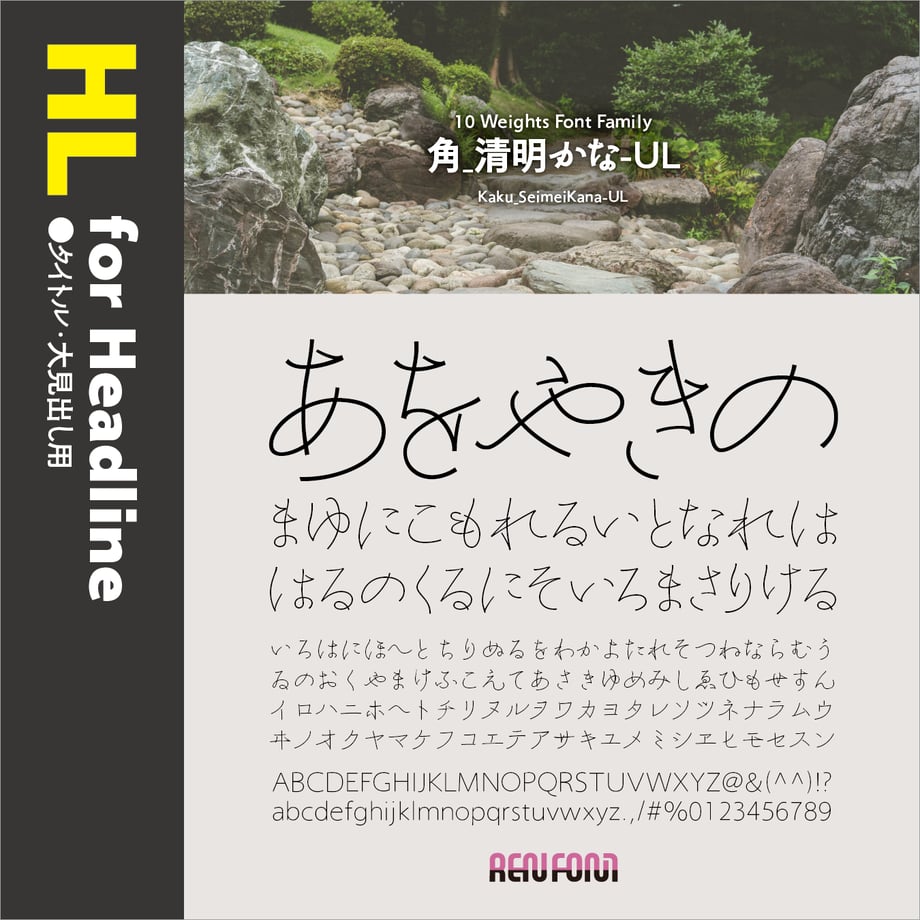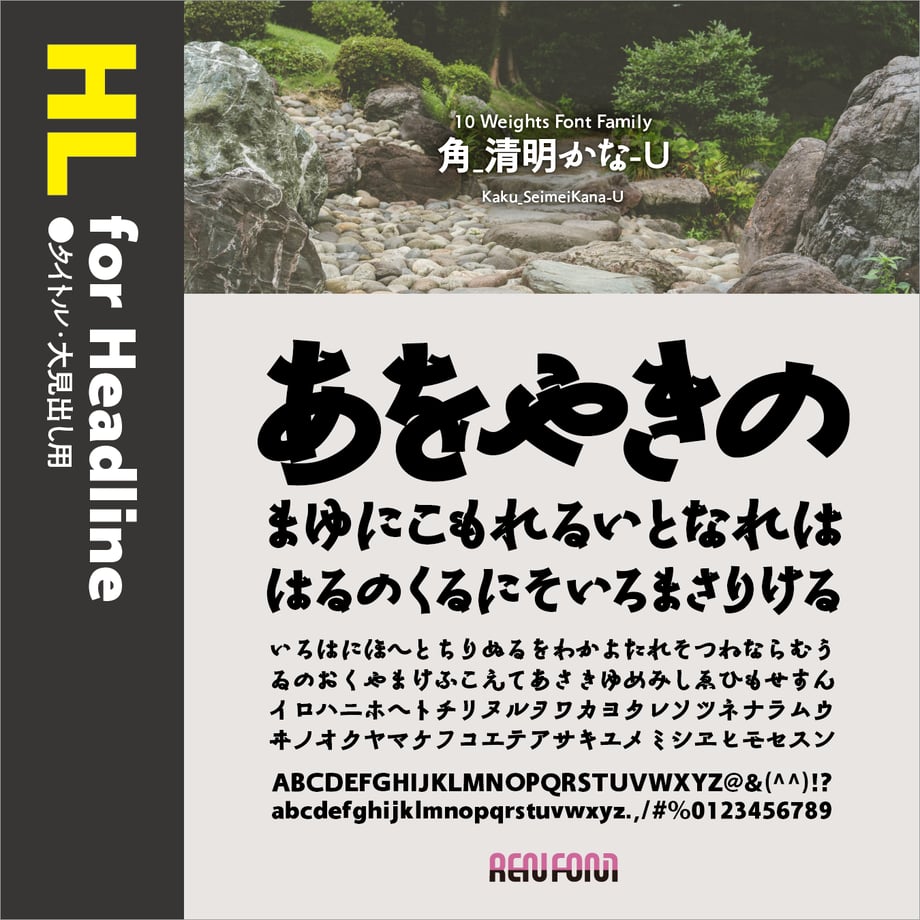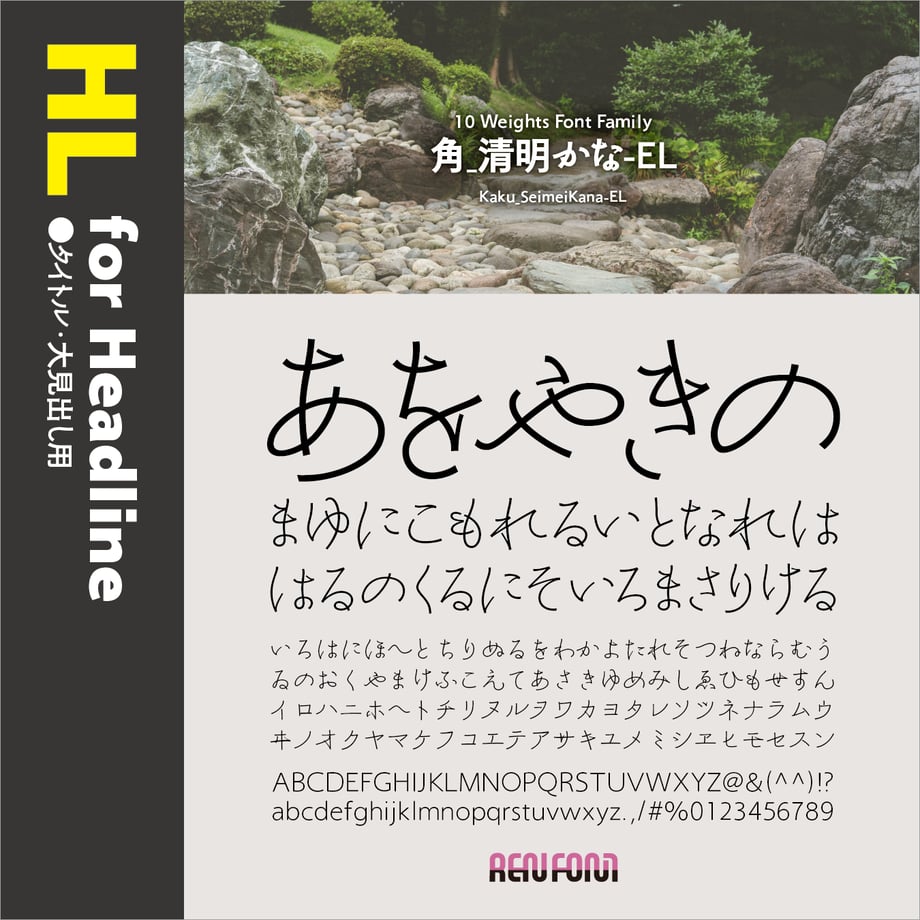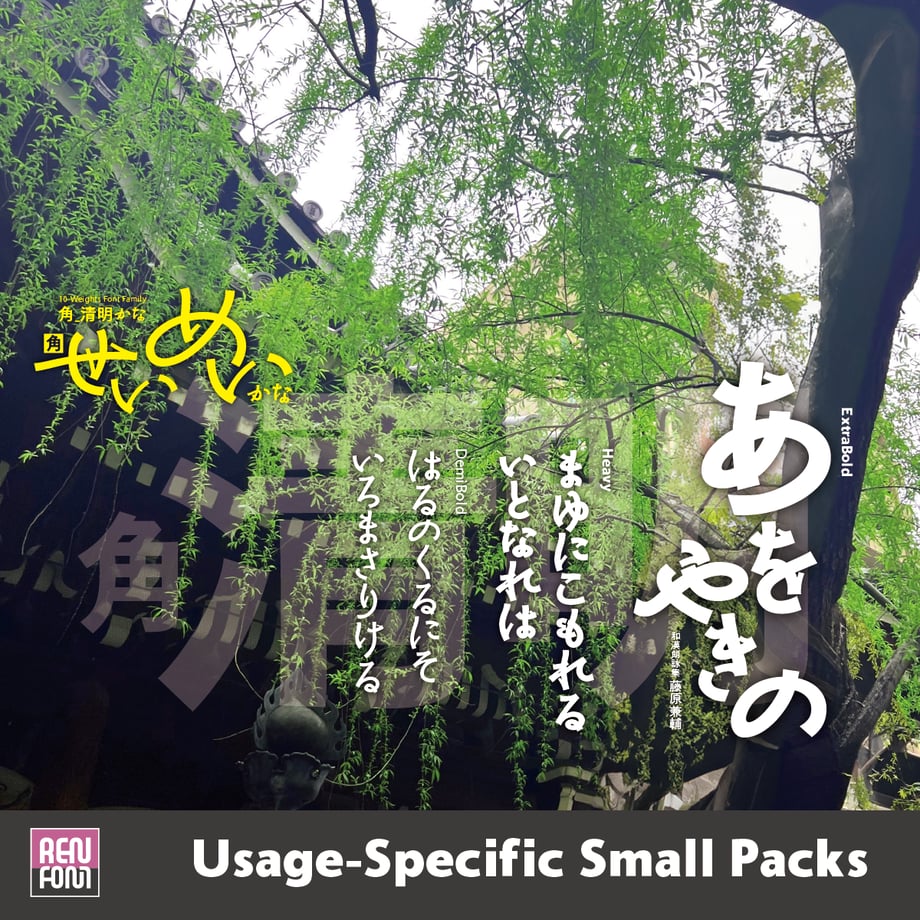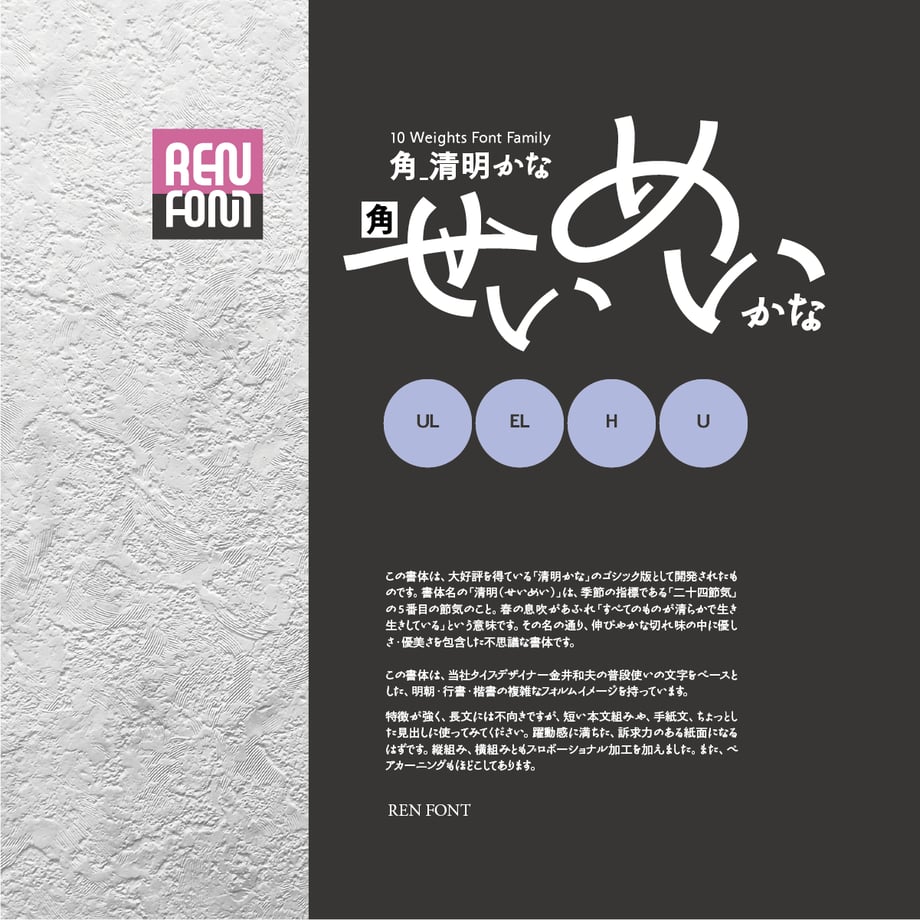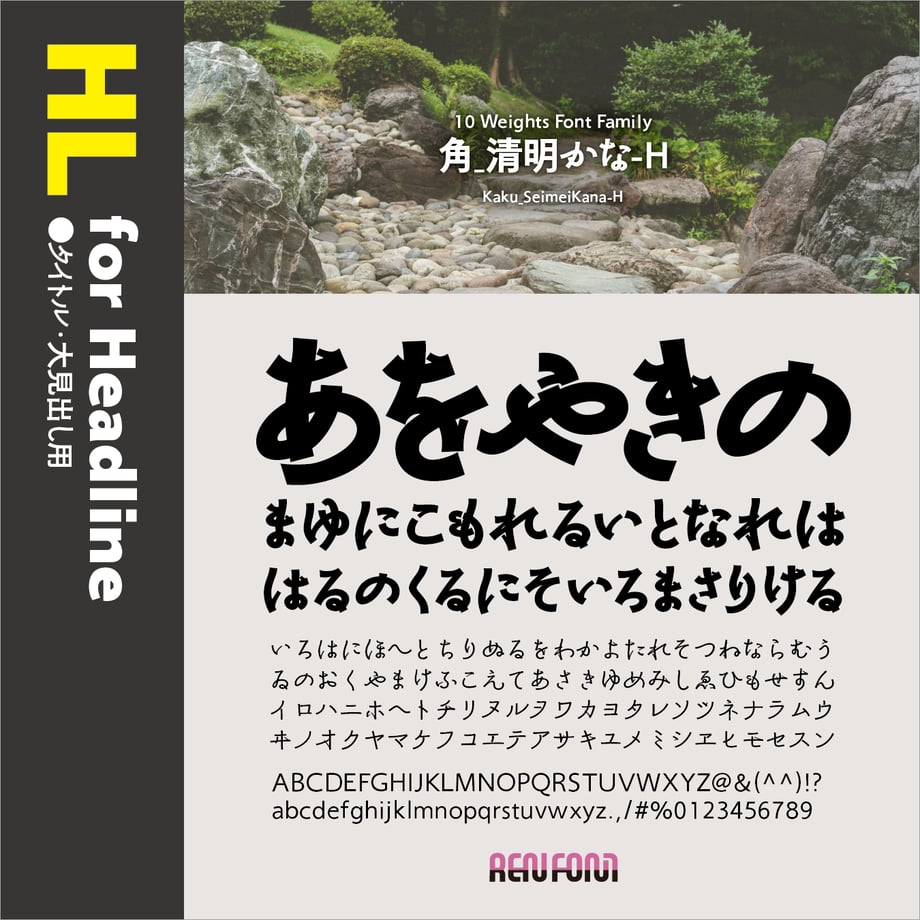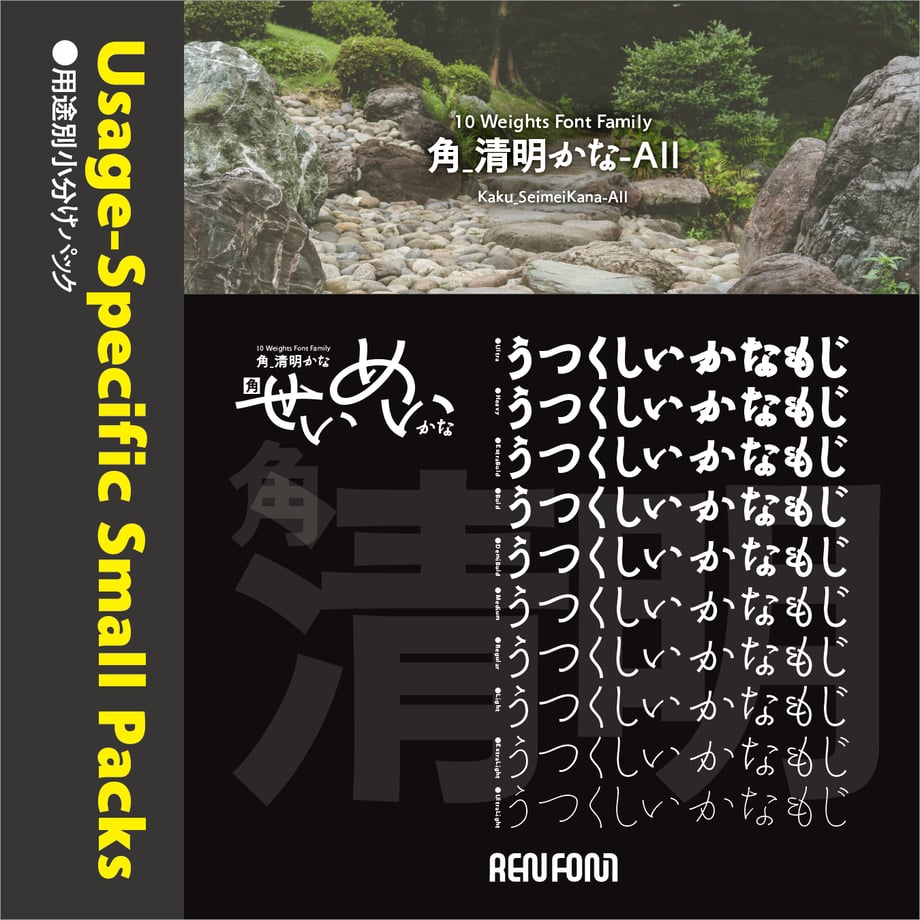
角_清明かな-HL(タイトル・大見出し用)UL/EL/H/U
優しさと切れ味をあわせ持つ
角_清明かな 10ウェイトフォントファミリー / OpenType
優しさと切れ味をあわせ持つ
この書体は、大好評を得ている「清明かな」のゴシック版として開発されたものです。
書体名の「清明(せいめい)」は、季節の指標である「二十四節気」の5番目の節気のこと。春の息吹があふれ「すべてのものが清らかで生き生きしている」という意味です。その名の通り、伸びやかな切れ味の中に優しさ・優美さを包含した不思議な書体です。
この書体は、当社タイプデザイナー金井和夫の普段使いの文字をベースとした、明朝・行書・楷書の複雑なフォルムイメージを持っています。「UL(ウルトラライト)」から「U(ウルトラ)」までの、合計10ウェイトで構成されています。
また、オールドなイメージを残しつつも、その概念にとらわれず大仮名に設計してあり、近代的な組版にも対応するマルチな性格を備えています。
躍動感と訴求力を表現する
角_清明かなファミリーの各書体は、クリエイティブワークに「躍動感と訴求力を表現する」一助にと開発されました。和文フォントは、正方形の中に押し込めることにより、伸びやかさがなくなる傾向があります。この書体は必ずしも正方形にとらわれない自由な発想で作られています。
特徴が強く、長文には不向きですが、短い本文組みや、手紙文、ちょっとした見出しに使ってみてください。躍動感に満ちた、訴求力のある紙面になるはずです。縦組み、横組みともプロポーショナル加工を加えました。また、ペアカーニングもほどこしてあります。
他社「総合書体」との「共存」
現在、世の中に出回っているフォントの数はすでに数え切れないほどになっています。ゴシック体に限ってもまた然り。
角_清明かなは10ウェイトありますが、それぞれの太さにさほどの差がありません。本来は7ウェイト展開にすべきかも知れませんが、あえて10ウェイトにしたのにはそれなりの理由があります。
かなフォントは、単独ではあまり存在意義はありません。漢字と組み合わせてはじめて「意味」が生じます。
フォントのウェイト呼称は、ほとんどのベンダが「ライト」から「ウルトラ」に至る7から9ウェイト展開をしています。ただ、それぞれの太さに明確な基準はなく、各ベンダの判断によります。ですので、例えば「ライト」でも太さが微妙に異なってきます。かなフォントがそれに対応するには、細かいウェイト展開が必要となります。
当社かなフォントの細かいウェイト展開は、それが理由です。お好みに合わせて合成フォントをお楽しみいただければ幸いです。
●UL[ウルトラライト]
日本語文章の約70%はひらがな、カタカナが占めているといわれます。それだけに紙面の雰囲気を左右し、決定づける重要なアイテムです。
角_清明かなのウェイトは10。本文用からタイトル・見出しに至るまで幅広い用途に対応します。中でも「UL(ウルトラライト)」「EL(エクストラライト)」は大きなタイトル見出しには絶大な効果を発揮します。極細ウェイトのある、AXIS、ヒラギノ角ゴシックにも対応できるよう設計してあります。
そのフォルムは、しなやかでなめらか。払いを強調して舞踊のような躍動感を表現しました。正統からギリギリ踏み外さないよう細心の注意を払った、優美な書体です。
欧文・数字は、どちらかというと奔放な両かなとは異なり、クセの少ない伝統的なイメージにデザインしました。わずかに「K」「Q」「R」のテールに「かな」の雰囲気を持たせてあります。
格調高いMyriad調の形状ですが、若干現代風な設計になっています。欧文書体としての単独使用にも十分に耐えうる、和文付嘱書体としては稀な、非常に高い完成度を持っています。